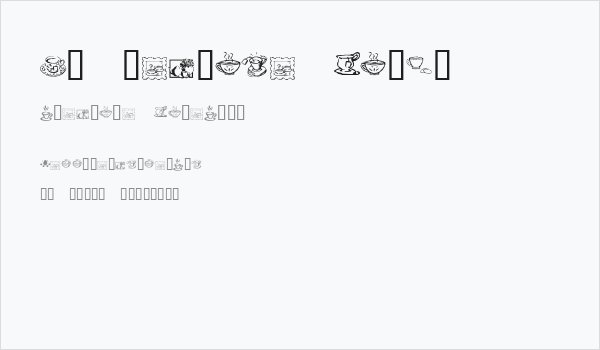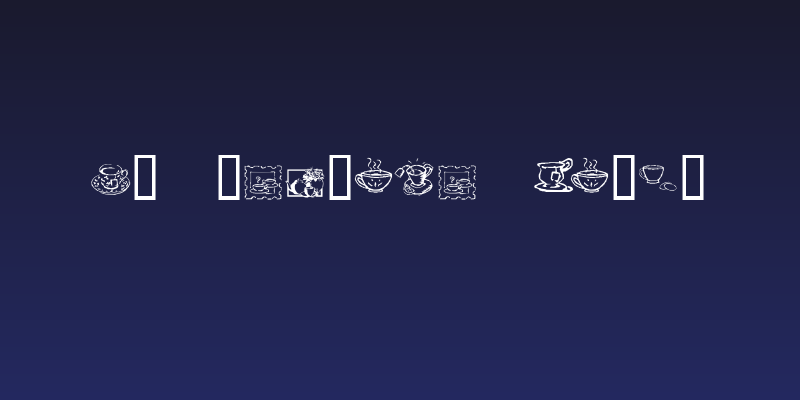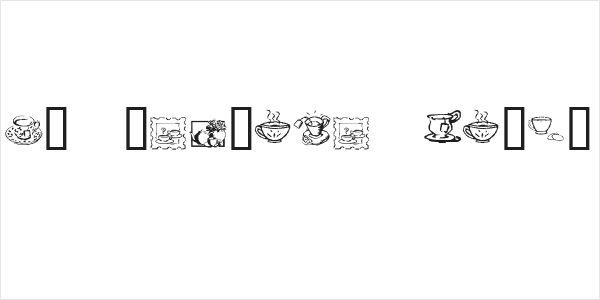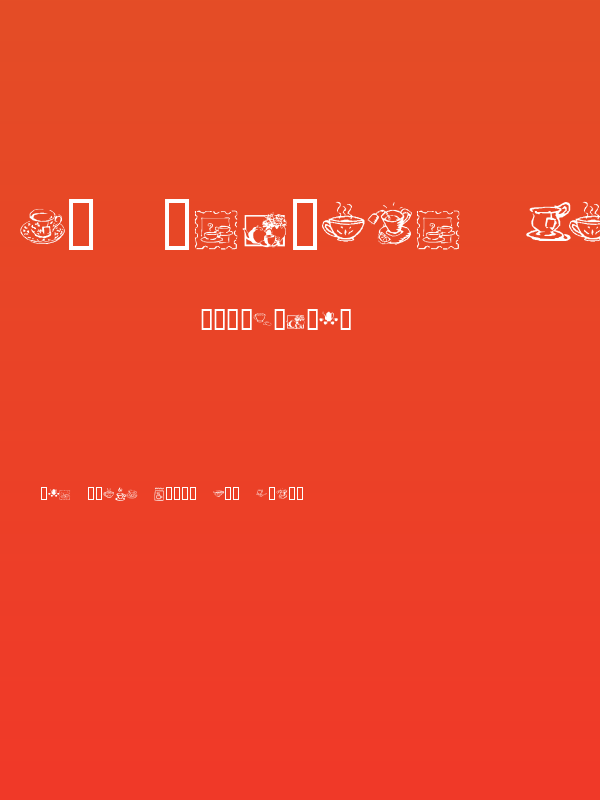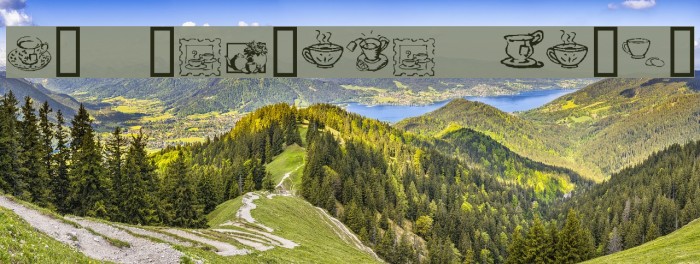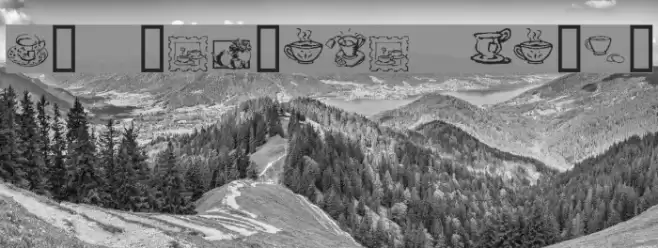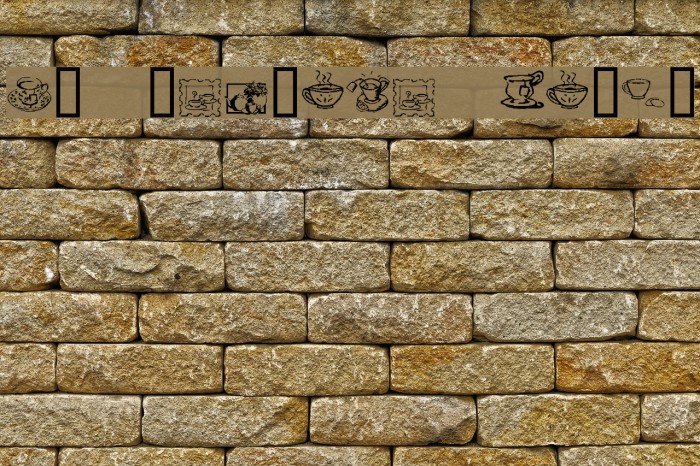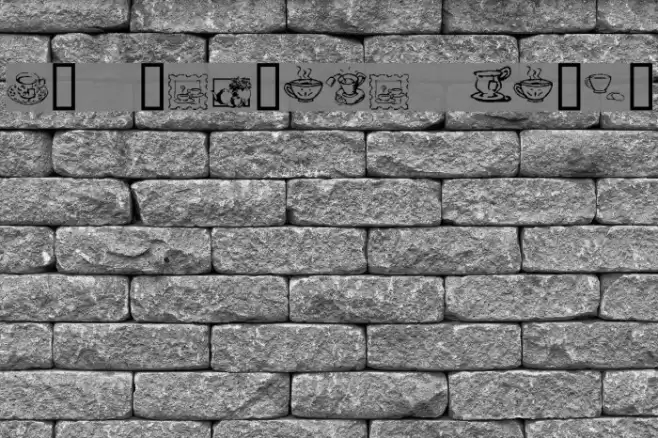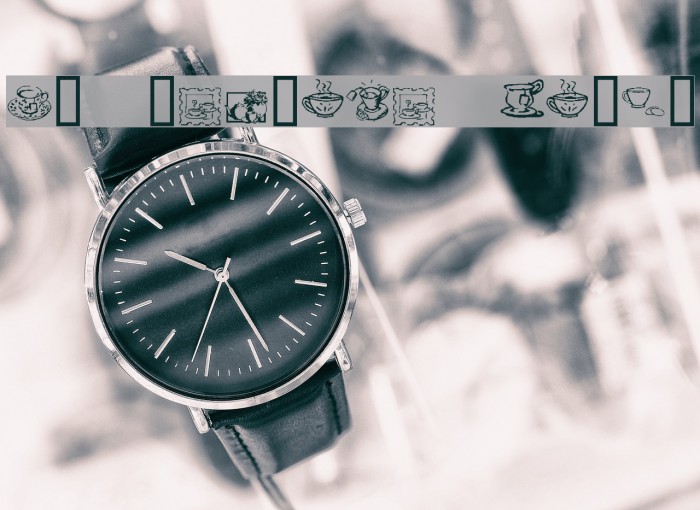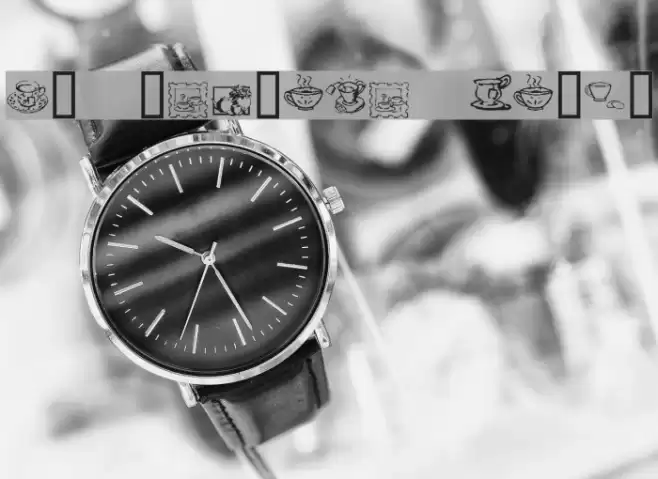
KR Teatime Dings Font
| Caso de uso | Logos, Decorative elements, Invitations |
| Projetos propostos | Ideal for tea party invitations, cafe menus, scrapbooking, and themed event decorations. |